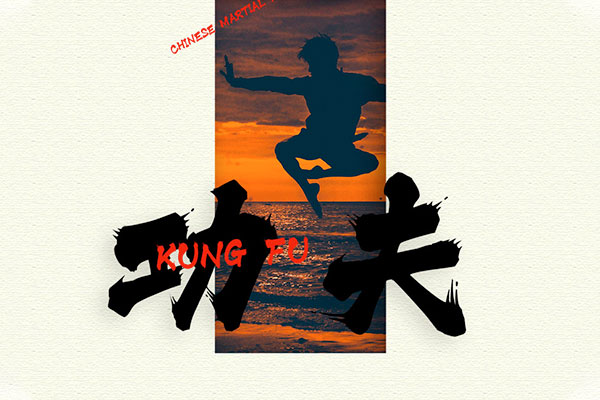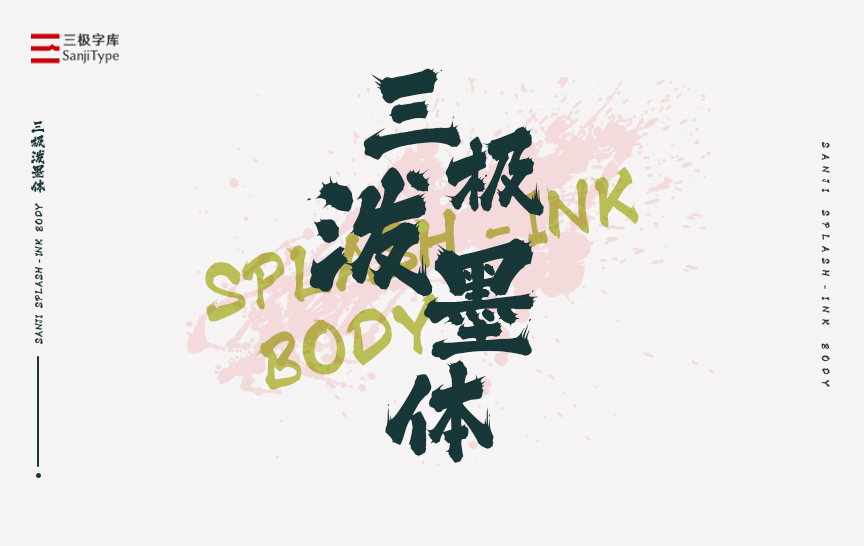
三极泼墨体
三极泼墨体:奔放不羁的字体新风尚
三极字库最近推出了一款免费商用的字体——三极泼墨体。这款字体以其独特的风格和强烈的视觉效果,迅速在设计师中流行开来。
三极泼墨体的字形设计独具一格,每一个字都仿佛是一幅泼墨画,充满了不羁和奔放的气息。这种设计风格不仅个性十足,而且能够为设计师的创意提供更多的发挥空间。
作为一款免费商用的字体,三极泼墨体覆盖了GB2312规定的6763个汉字,为设计师们提供了更为全面的选择。
三极泼墨体效果预览